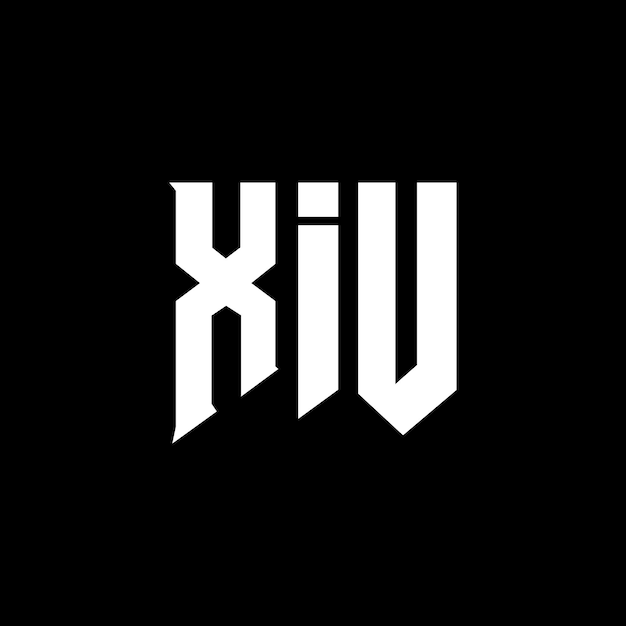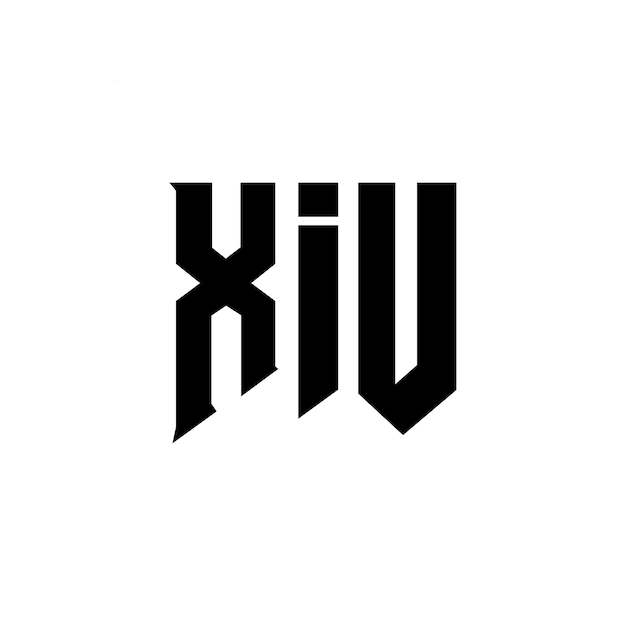
XIV conception de logo en lettres pour une entreprise de technologie XIV conception du logo en combinaison de couleurs noir et blanc XIV logo XIV vecteur XIV conception XIV icône XIV alphabet XIV typographie